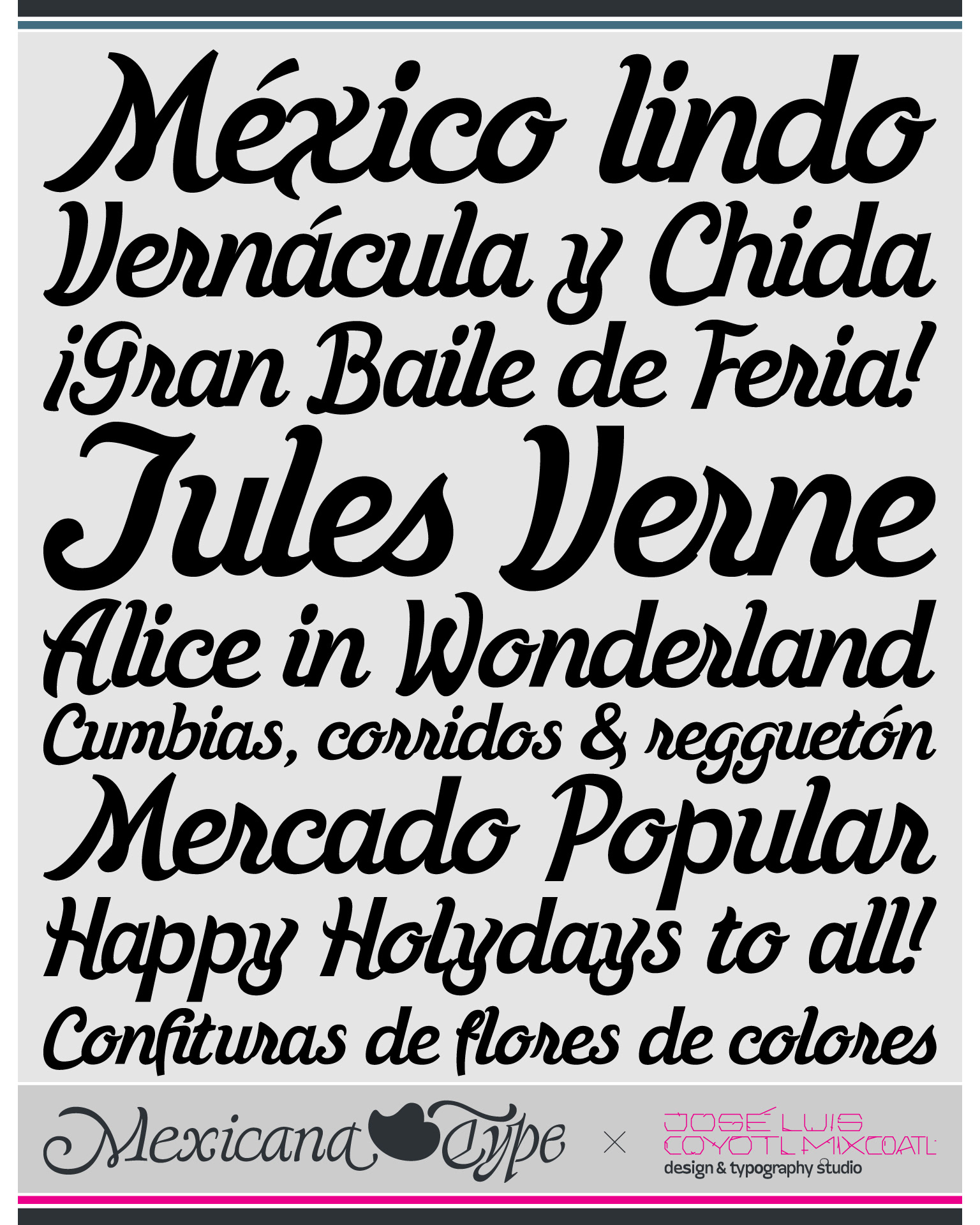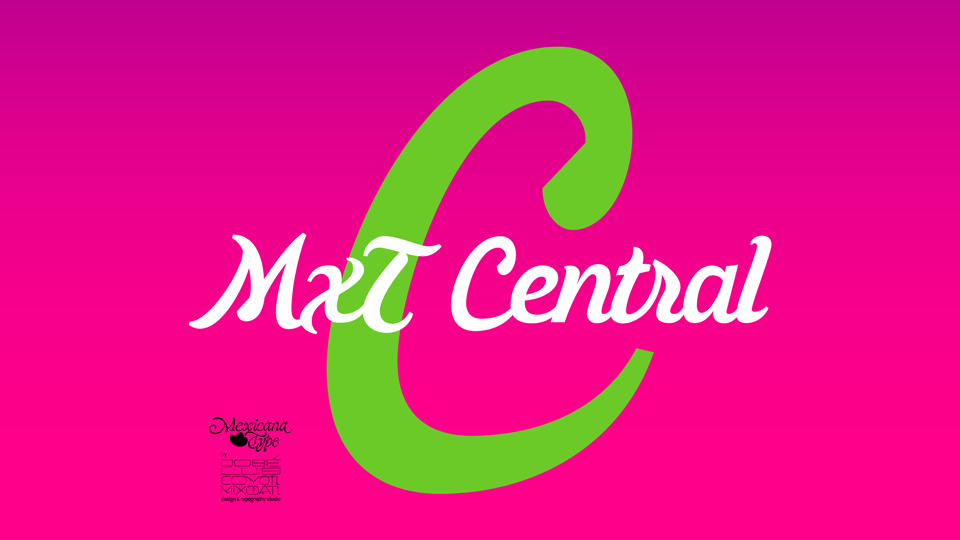
Mxt Central es una fuente que viene de el desarrollo con un perfil mucho más limpio y estético de MxT Santanera, que tienen la base formal y conceptual de letras vernáculas mexicanas, de la letra rotulada pintada a mano principalmente en entornos de cultura popular como mercados, la Centrales de Abasto, camiones de antaño, pero ahora con un sentido un poco más dinámico y estilizado, desarrollado con un estilo script, lo que en conjunto le da un aspecto asimétrico y contrastado en sus formas, con unas mayúsculas/altas que tienen una linea base que baja un poco para darle un cuerpo a los textos un tanto más dinámicos. Con un diseño completamente dinámico  que no abre mucho espacio a los trazos rectos, sus curvas la definen y generan una amplia gama de contraformas y contrastes juguetones, con remates de curvas y extensiones muy diversas sin perder cierto sentido experimental en sus formas y en su conjunto en la mancha tipográfica, haciendo de esta tipografía una display con muchas posibilidades en su uso y aplicación.